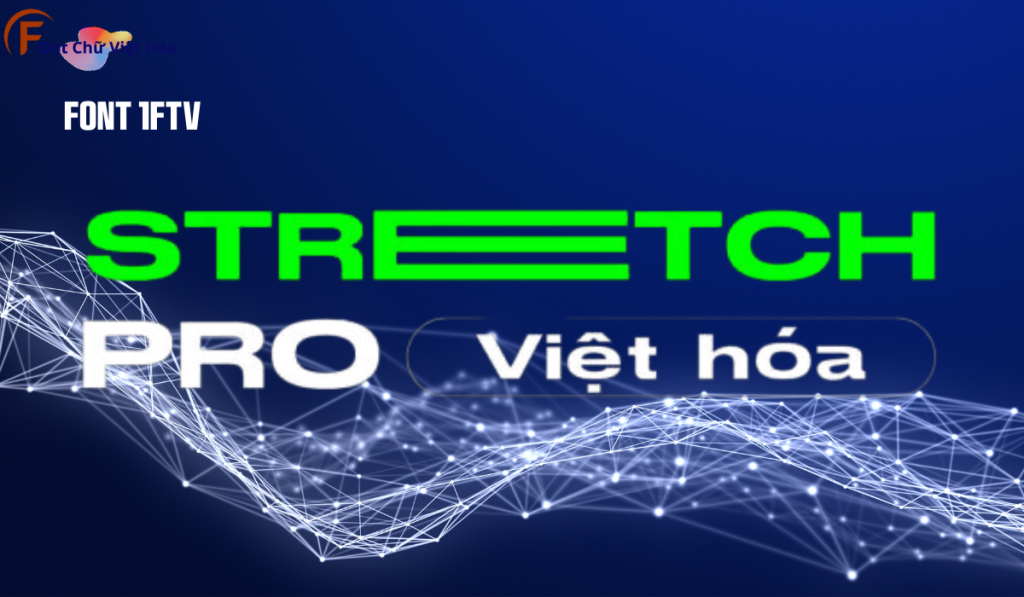
Font 1FTV Stretch Pro
Tác giả: 1FTV Studio
Bộ Font: 1FTV
Độ dày: Light, Regular, Medium, Bold
Font 1FTV Stretch Pro là một font chữ độc đáo thuộc bộ 1FTV, nổi bật với phong cách sans-serif hiện đại và các đường nét kéo dài, mảnh mai. Thiết kế của 1FTV Stretch Pro tập trung vào sự thanh thoát, tạo cảm giác sang trọng và tinh tế, đặc biệt phù hợp cho các thiết kế đòi hỏi tính thẩm mỹ cao như poster, logo, và tiêu đề. Với tỷ lệ chữ dài và hẹp, font này tạo ra ấn tượng thị giác độc đáo và giúp tối ưu hóa không gian trong thiết kế. Font này cũng đã được Việt hóa, mang đến sự linh hoạt và tiện dụng cho các dự án thiết kế bằng tiếng Việt.